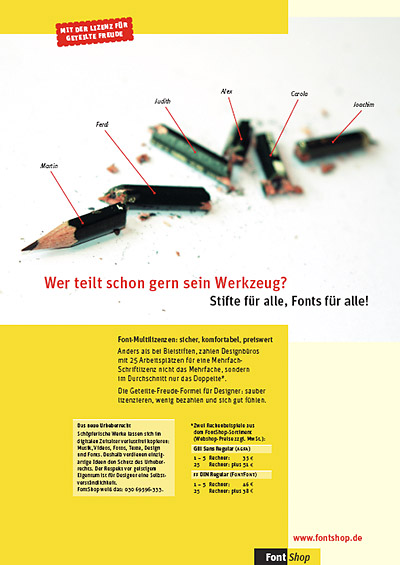
Neue FontShop-KampagneWenn ein Song im Radio läuft, bekommen Komponist und Texter Tantiemen.
Wenn Deine Schrift auf einem SPIEGEL-Titel erscheint oder ein Bestseller damit
gesetzt wird, bekommst Du nichts. Das ist ungerecht, aber
rechtsmäßig: Die Darbietung und Vervielfältigung von
Schriftsatz ist abgabenfrei. Nicht legal ist die Benutzung unlizenzierter
Schriften im Designbüro. Dies ärgert Schriftentwerfer und auch
![]() Beispiel Harry Potter und der Orden des Phönix (Band 5),
britische Ausgabe: Leser im Königreich äußerten sich empört über
den schlechten Druck, die Bindung und die verwendete Schrift. Die Type der
US-Ausgabe sei größer, kräftiger und klarer (»larger,
fuller, and clearer«). Kein Wunder, denn das Buch war in einer modernen
Fassung der Buchschrift Garamond gesetzt, und zwar in der Adobe Garamond, 1989 gezeichnet und
digitalisiert von Robert Slimbach. Sie ist perfekt abgestimmt auf moderne
Druckverfahren, zum Beispiel Rollen-Offset. Die UK-Ausgabe bediente sich einer
zu leichten und schwer lesbaren Garamond, deren Proportionen auf Vorlagen
für den Bleisatz basierten.
Dank Robert Slimbach haben die US-Leser ihren Harry Potter schneller verschlungen als die Briten: Die Augen ermüdeten weniger rasch, das Lesetempo war höher aufgrund der schneller zu erfassenden Wörter. Leider wird Slimbachs Beitrag zum Genuss des Romans kaum honoriert. Während die Autorin Joanne K. Rowling, die Illustratorin Mary GrandPré, die Druckerei, der Papierhersteller, der Buchhändler pro verkauftem Buch ihren Anteil erhalten, geht der Schriftentwerfer leer aus. Allein die Setzerei, die den Text des Romans erfasst und umbrochen hat, zahlte (hoffentlich) eine Nutzungslizenz für die Adobe-Garamond-Familie. Ob sie mit der Schrift einen Bestseller oder eine Visitenkarte gestaltet, hat auf den Lizenzpreis genauso wenig Einfluss wie die wiederholte Verwendung der Schrift, denn einmal lizenzieren heißt: für alles und so oft man will verwenden dürfen. Schön für die Schriftbenutzer, weniger schön für die Schriftentwerfer. Richtig angeschmiert sind die Schriftkünstler, wenn die Benutzer ihrer Fonts die erforderliche Nutzungslizenzen schlicht ignorieren, sprich: mit einer Raubkopie arbeiten oder die kommerziellen Fonts wie Freeware kopieren und weitergeben. FontShop-Gründer Erik Spiekermann kann ein Lied davon singen. Seit 30 Jahren entwirft er Schriften, denen er überall auf der Welt begegnet: FF Meta, ITC Officina, FF Info und FF Unit. Komischerweise fließen die Tantiemen für die »Bestseller« immer spärlicher. Jüngst fragte er einen befreundeten Designer, ob er denn seine Schrift, die der Drucksache den letzten Schliff gab, auch lizenziert habe. Die Antwort: »Vergessen ... hole ich nach«. ![]() FontShop-Gründer Erik Spiekermann ist Schriftschöpfer und Schriftbenutzer. Er hat für vieles Verständnis, aber Kollegen zu beklauen findet er »unter aller Kanone«. (Foto: Fontblog) »Ich kann ja verstehen, wenn ein Kollege den ein oder anderen Font ›ausprobiert›, der ›irgendwie› den Weg auf seine Festplatte gefunden hat.« bemerkt Spiekermann augenzwinkernd. So was passiere, er stehe selbst mit beiden Beinen in der Berufspraxis. In dem Augenblick jedoch, wo mit einer Schrift ein kommerzielles Projekt produziert werde – egal ob für eine internationale Marke oder den Bäcker nebenan – sei eine Lizenz fällig. »In diesem Fall berechnet der Kollege Geld für seine Leistung, die meine Leistung enthält. Doch etwas weiter zu verkaufen, das man selbst nicht legal erworben hat, ist kein Kavaliersdelikt sondern Diebstahl.« Schriftlizenzen kosten nicht die Welt. Eine neue FontShop-Anzeigenkampagne widmet sich dieser frohen Botschaft. Jeder Designer sollte mit einer legalen Schriftlizenz seine Jobs gestalten. Ein komplettes Designbüro (oder ein Großunternehmen) sauber mit Schriftlizenzen auszustatten, kostet nur einen Bruchteil der Lizenzen für Anwendungssoftware (vgl. Rechenbeispiel am Ende dieses Beitrags). Eine Multilizenz ist für die Schriftentwerfer der bescheidene Ersatz für die nicht vorhandene GEMA. Wenn die Darbietung und Vervielfältigung gedruckter Schriften schon abgabenfrei ist, dann sollten große Setzereien, Designbüros und Unternehmen, in denen viele Menschen mit einer Schrift arbeiten, diese wenigstens für alle Arbeitsplätze lizenzieren. Die neue FontShop-Anzeige zum Thema Schriftlizenzen: ![]() Aktuelle FontShop-Anzeige zum Thema Multilizenzen, soeben erschienen in PAGE 10/2005 (Agentur: Studio Adhoc) Ausschnitt FontShop-Anzeige, Beispielrechnung: ![]() Vergrößerter Auszug FontShop-Anzeige: So preiswert sind Multilizenzen für Schriften Herausgegeben: Mo - September 5, 2005 at 11:03 vorm. | |